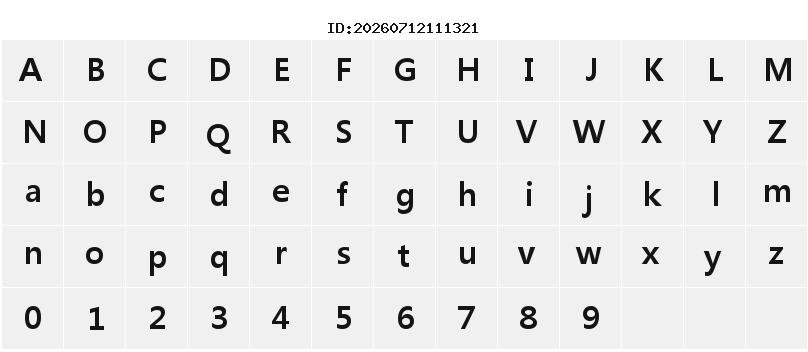
• Font Name: 맑은 고딕
• Designer: 이경배; 김대권
• Manufacturer: Microsoft Corporation
• Description: 맑은 고딕은 ClearType 기술을 채택하여 개발한 한글 폰트이며, 특히 스크린 상에서 뛰어난 가독성을 제공한다. 기본 모듈은 훈민정음의 글자체를 기반으로 제작하였으며, 모던한 자형과 곧고 잘 정리된 획을 사용하여 현대적인 감각을 부여하였다. 글자의 속공간을 알맞게 확보하여 작은 크기에서도 판독성을 높였으며, 고른 자간과 시각 중심선으로 가독성을 극대화하였다.
맑은 고딕.ttf is a modern, elegant sans-serif font designed for ultimate readability and visual harmony. Perfect for branding, headlines, web design, and print materials.